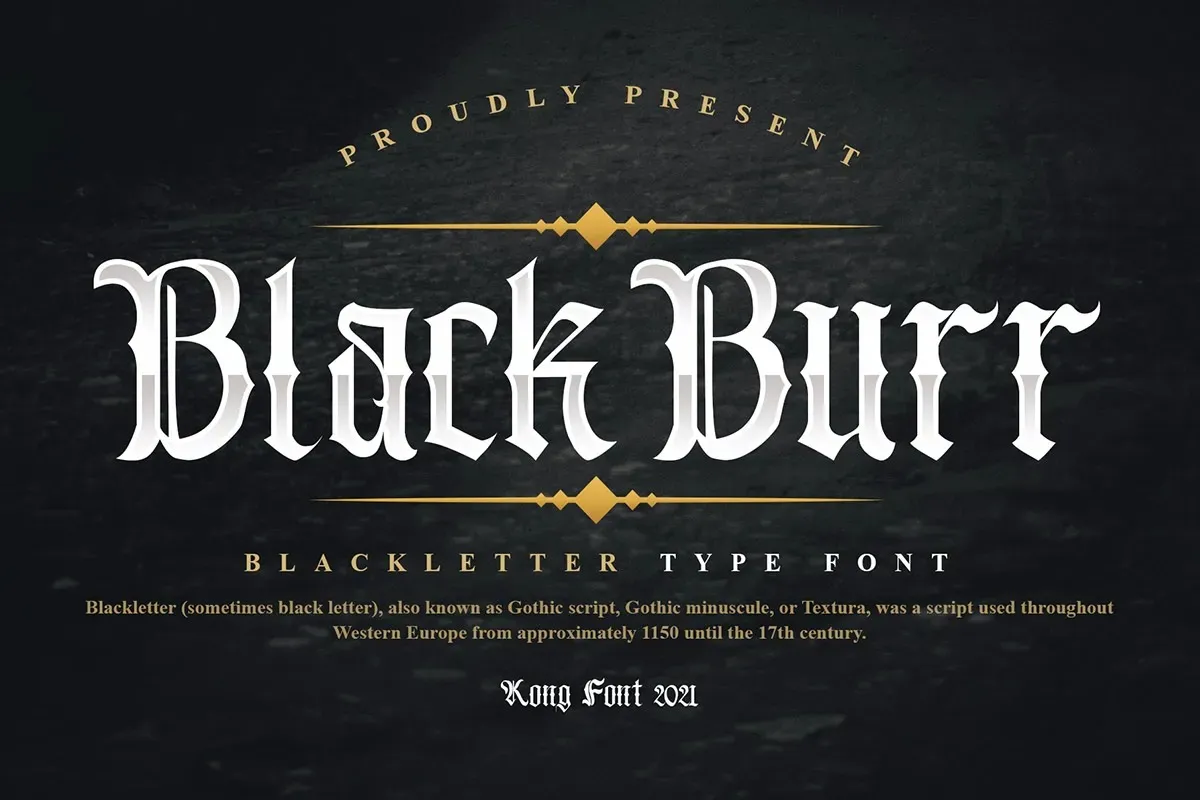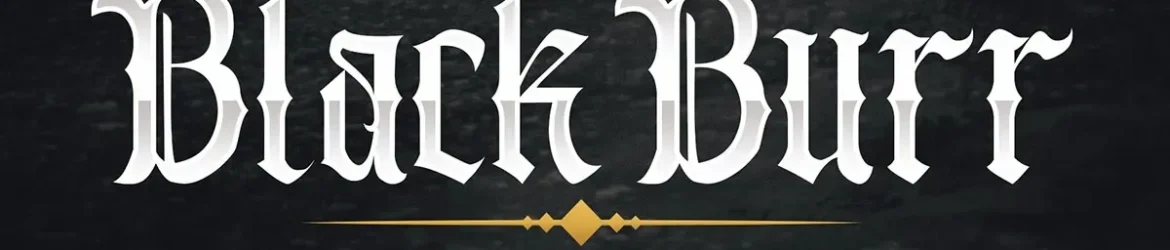
A Blackburr Font é uma nova adição à nossa gama de tipos de letras modernas inspiradas no antigo estilo chamado blackletter. Desenvolvida pelos talentosos designers da plataforma 99designs, esta fonte foi projetada especificamente para ambientes onde o estilo do blackletter se destaca, como lojas de tatuagem, camisetas personalizadas, selos de embalagens e rótulos de bebidas. Sua simplicidade clássica faz dela uma opção ideal tanto para uso em aplicações digitais quanto impressivas, como a cara das tatuagens ou o topo do seu drink de festa. Além dos caracteres básicos da língua latina, a Blackburr Font também inclui um conjunto adicional de elementos gráficos para decorar suas criações. Estes detalhes chamativos e elegantes são perfeitos para personalizar designs ou fazer uma impressão impecável em qualquer aplicação visual onde desejará destacar o seu estilo único. Seja você designer, artista ou criador de conteúdo digital que busca adicionar um toque de elegância clássica a seus projetos, a Blackburr Font é sua escolha certa. Combinando modernidade com tradição através do uso deste tipo de letra, você pode criar peças que destacarão e encantarão seus espectadores sempre.